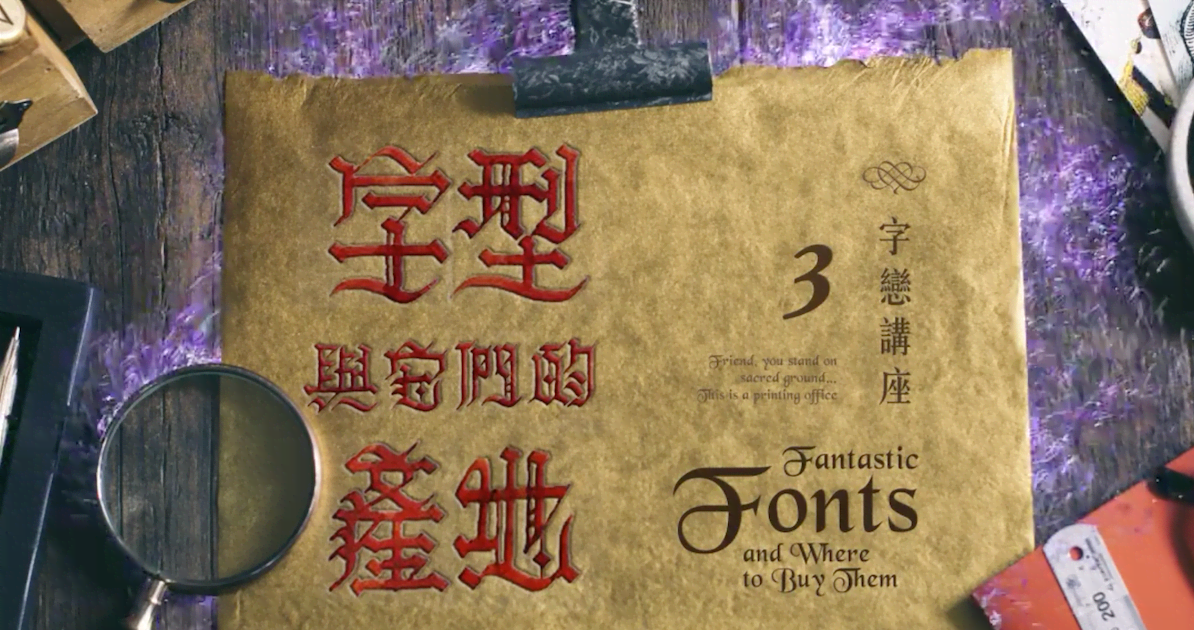
【字戀講座在華山 #3】字型與它們的產地
字戀講座是
由 justfont 主辦、籌劃的全新免費字型講座,
除了希望能推廣字型相關知識外,
也希望讓大家更深入瞭解字型設計的文化、歷史、技術、哲學⋯⋯
每次講座前半場,都會帶給大家台灣民眾必修的基本的字型知識,
也會在後半場依照時事、互動調查需求來規劃有趣的次領域主題,
希望能用輕鬆好玩的方式,讓大家更親近這個與我們息息相關的領域。
講座介紹
「請問這是什麼字體?」
「安安?你這字體是從哪裡買的?」
「要怎麼看出字體來自哪個國家?」
「安安你字型系?」
第三場主題:字型與它們的產地
字型與它們的產地,設計師冒險前傳,脫麻就靠這一次!
我們請到奇異字體學教授帽子哥,講授他從前的學院課程
例如架構:漢字九宮格、歐文五線譜,甚至歷史
更要告訴你去哪捕(ㄍㄡˋ)獲(ㄇㄞˇ)美字怪獸
身為字體麻瓜的你還沒搞懂神奇字型嗎?
讓字體學教授打通你的任督二脈吧!
主題目錄:
★ 字型有哪些分類?
★ 怎麼看字型的發源地?
★ 了解字型的故事後,怎麼應用?
★ 怎麼持續學習累積字型的知識?
★ 看到喜歡的字型,怎麼才能合法取得?
講座亮點:
★ jf 金萱設計師群現身說法
★ 從身邊出發,深入淺出的講座主題
講座難度
★☆☆  初學者適合,高手可複習